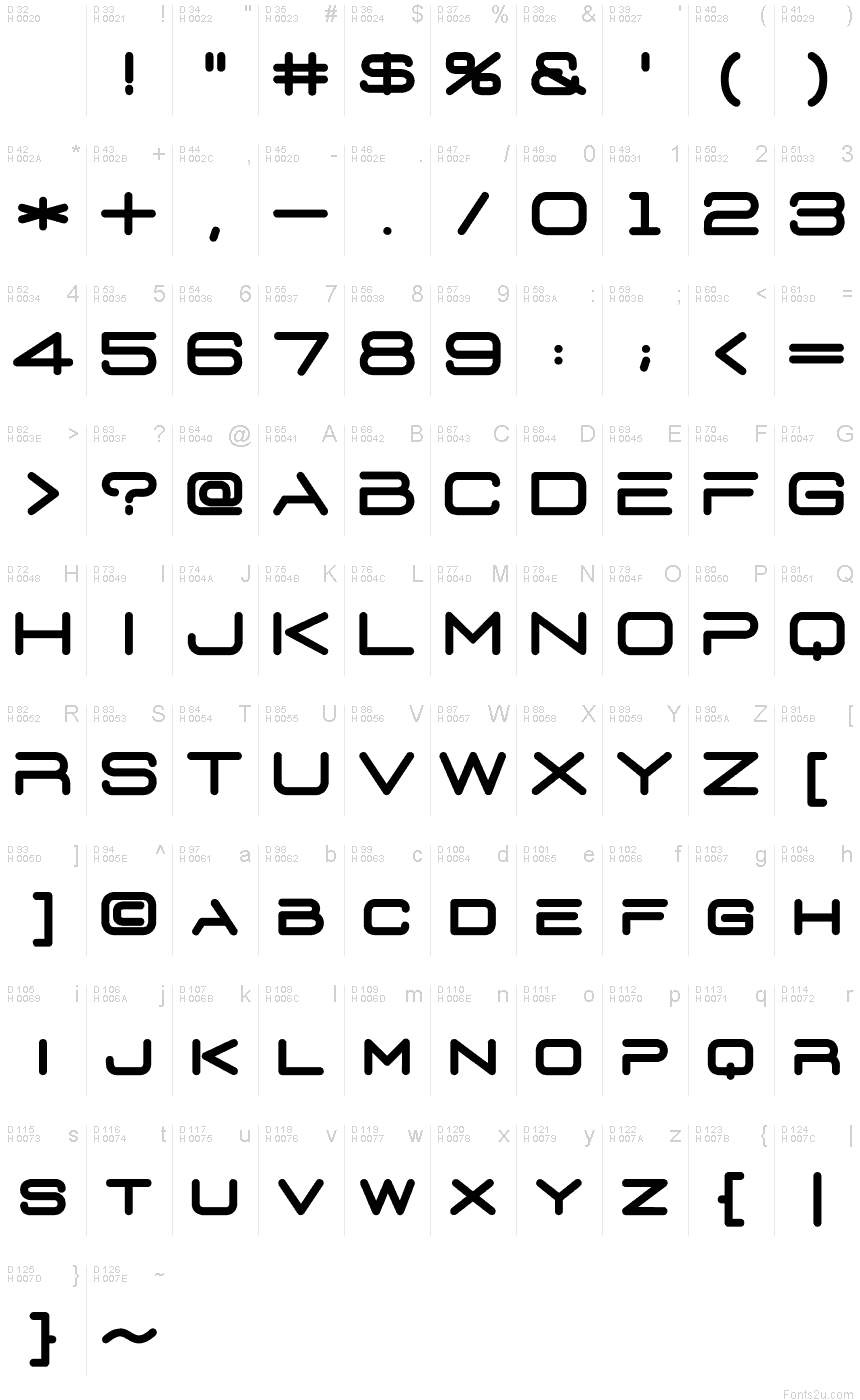
Krój pisma D3 Euronism Bold od DigitalDreamDesign łączy masywny, zaokrąglony szkielet w stylu techno z płynnymi, ciągłymi liniami, nadając całości elegancki sznyt science-fiction. Kwadratowe krzywe i monolinearna konstrukcja sprawiają wrażenie zaprojektowanych z precyzją, a nie ręcznie szkicowanych, dzięki czemu nagłówki układają się jak elementy przejrzystego interfejsu. Ten darmowy font świetnie sprawdzi się wszędzie tam, gdzie potrzebujesz wyrazistego, futurystycznego wyrazu, który mimo wszystko pozostaje przyjazny i przystępny.
Wykorzystaj D3 Euronism Bold w logach gier, grafikach e-sportowych, plakatach technologicznych, ekranach powitalnych aplikacji, opakowaniach produktów i odważnych nagłówkach UI. Ten darmowy font doskonale prezentuje się w dużych rozmiarach, gdzie zaokrąglone rogi i zwarty rytm naprawdę robią wrażenie. W przypadku mniejszych tekstów uzupełniających, świetnie komponuje się z prostym krojem bezszeryfowym.
D3 Euronism Bold